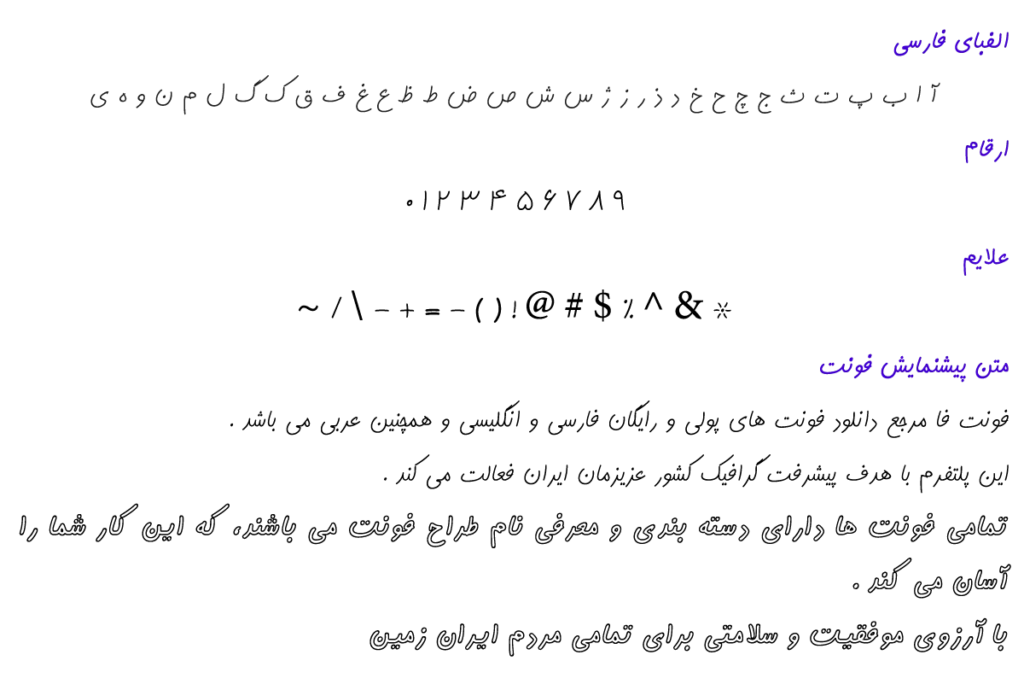
فونت فارسی کامران – Far Kamran
مجموعه فونت: فونت سری Far
طراح فونت: ابوالفضل سيل سپور نوع فونت: فونت دست نویس
پیشنمایش فونت کامران
توضیحات و معرفی فونت کامران
فونت فارسی کامران ( Far Kamran ) از مجموعه فونت های سری Far می باشد، همچنین نوع فونت دست نویس می باشد.
فونت فوق العاده زیبای معرفی شده توسط ابوالفضل سيل سپور در سال 1390 بر اساس دستخت آقای کامران انصاری طراحی و ساخته شده است.
همچنین فونت در 3 وزن پر رنگ و معمولی است.
در لیست زیر می توانید وزن های این فونت فوق العاده زیبا را ببینید.
- Far Kamran Bold
- Far Kamran Regular
- Far Kamran Outline